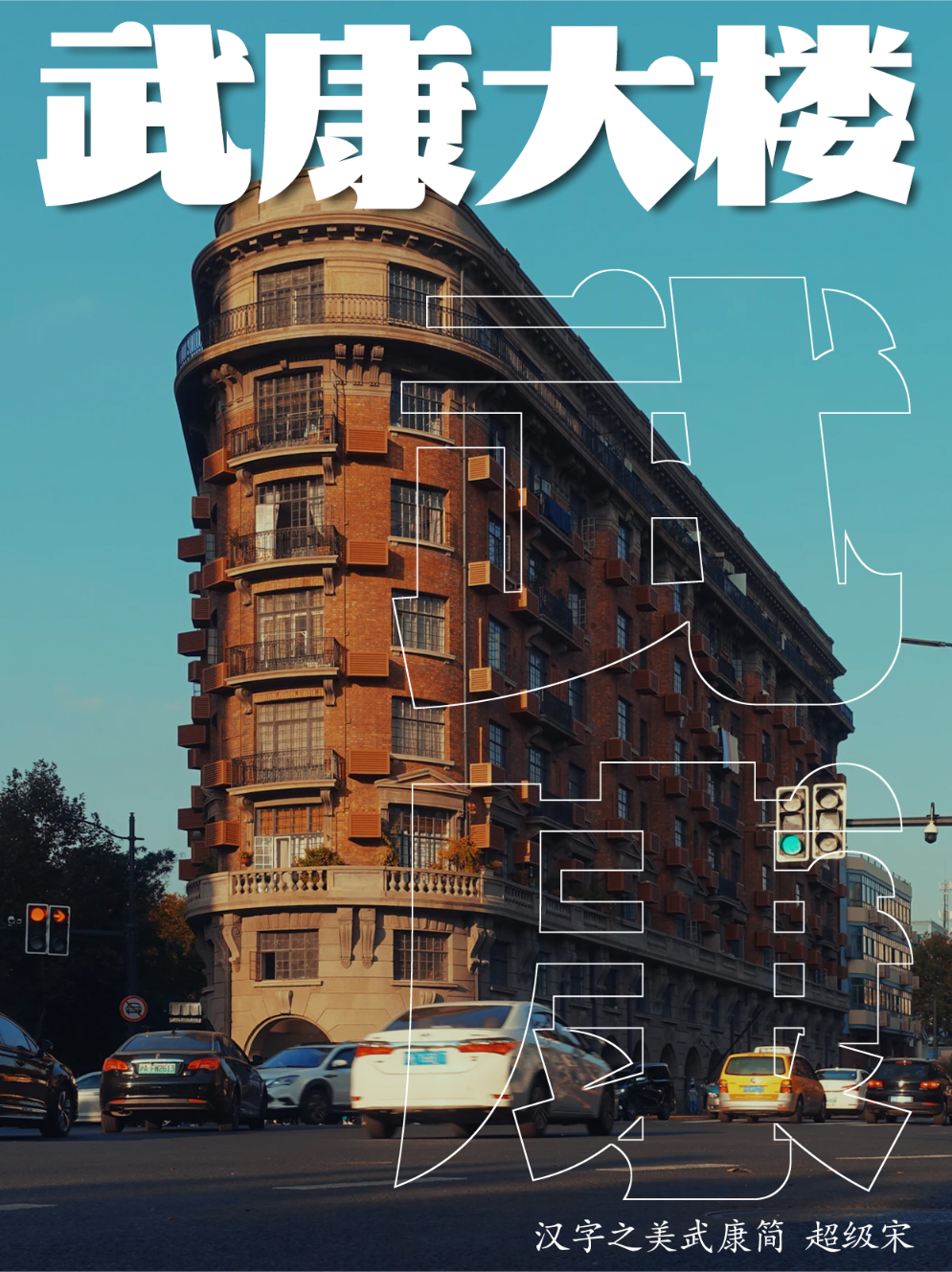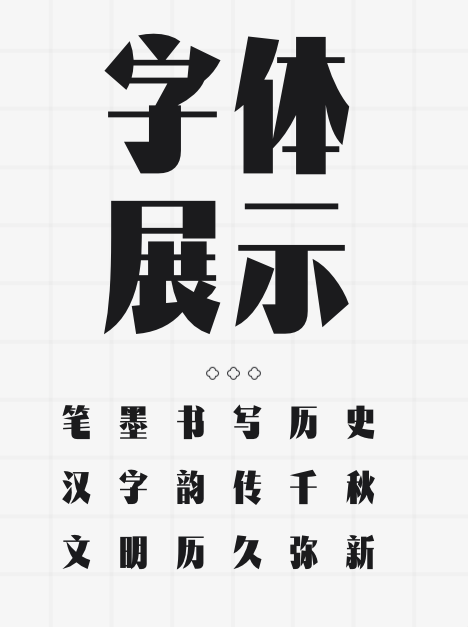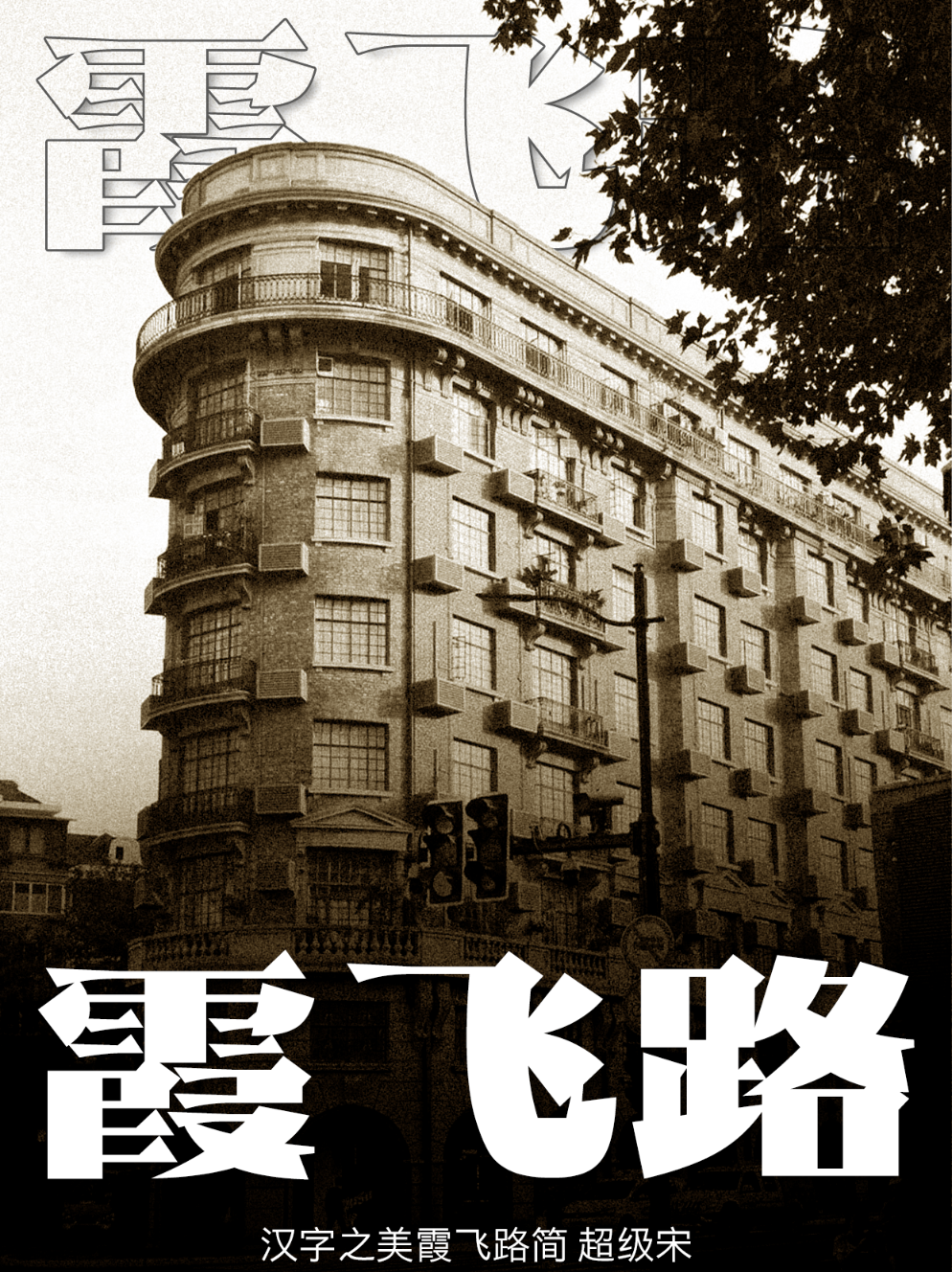
🎉复古风情大赏!老上海字体界的三大绝美代表,让你的设计一秒穿越回黄金时代✨
🌟 第一款推荐:汉字之美·霞飞路简
一提到老上海,怎能不提霞飞路(今淮海路)的繁华?这款“汉字之美·霞飞路简”字体,就像是从那个摩登时代走来,带着一丝丝复古的韵味与现代的简约。笔画间流露出的优雅,仿佛能听见远处电车“当当”的声响,让你的设计作品瞬间拥有了一种难以言喻的上海风情。👗🚃
🌟 第二款推荐:汉字之美·武康简
武康路,一条承载着无数故事的老街,而这款“汉字之美·武康简”字体,正是对这条历史街道的完美致敬。字体设计融合了老上海的建筑元素与现代审美,每一笔都透露着历史的沉淀与文化的韵味。用它来书写邀请函、海报或是品牌文案,都能让你的作品散发出独特的文化气息,让人回味无穷。🏠📜
🌟 第三款推荐:汉字之美·上海简
说到老上海,怎能不提“上海”二字本身?这款“汉字之美·上海简”字体,以简洁流畅的线条勾勒出上海的摩登与经典。它既保留了老上海字体的韵味,又融入了现代设计的简洁明快,无论是用于广告招牌、包装设计还是社交媒体文案,都能让你的内容在众多信息中脱颖而出,成为一道亮丽的风景线。🌆🎨
三款字体,三款风情,每一款都承载着老上海的故事与记忆。选择它们,让你的设计作品不仅仅是视觉上的享受,更是心灵上的触动。💖🎨